Красивая 3D надпись карандашом. Пошаговый урок
Сегодня мой любимый урок! Мы научимся рисовать 3D текст.
Вы помните, как здорово начинался первый фильм о Супермене? (Правда фильм вышел в 1978г). На нем очень классная супер гладкая надпись – отличный пример угловой перспективы.
Другой пример: вы помните открывающую сцену Звездных войн, где боевой корабль вплывает в кадр сверх и, кажется, никогда не закончится? Это отличный пример фронтальной перспективы.
Сегодня мы изучим один из стилей написания 3D текста. Для этого мы будем использовать угловую перспективу, потому что это наиболее сложно, наиболее интересно, и лучше всего смотрится. Потом вы можете поэкспериментировать с более длинными словами.
Давайте начнем с короткого слова «Hi».
1. Легко проведите линию горизонта через весь лист бумаги. Поместите по краям точки свода. (Если вам непонятны какие-то термины, то для начала следует пройти урок основ построения угловой перспективы).
2. Проведите в центре вертикальную линию.
3. Легко соедините точки свода с верхним и нижним концом вертикали.
4. Определите лицевую ширину букв. Убедитесь, что ближняя буква шире. Это отличный пример размера. Буква, которая должна быть ближе, автоматически должна быть нарисована больше, следуя направляющим линиям. Это будет еще более важно, когда вы будете рисовать три или больше букв в будущем.
5. Нарисуйте форму буквы “H” строго следуя опорным линиям. Помните как важны вертикальные линии. Теперь присмотритесь к боковым сторонам листа и вертикальной линии в центре, чтобы убедиться, что “Н” правильной формы.
6. Теперь начните выводить букву “I”. Сейчас вы можете ясно видеть, какую роль играет размер в визуальном восприятии 3D изображений.
7. Легко прочертите опорные линии к правой точке свода, чтобы обозначить ширину буквы.
8. Установите толщину буквы “I” двумя точками. Соедините эти две точки вертикальной линией.
9. Завершите букву “I” вертикальной линией ножки. Теперь тщательно прорисуйте все углы буквы “H” справа.
10. Определите позицию света и затените противоположные поверхности. Сотрите все лишние линии.
УРОК 27: ПРАКТИЧЕСКОЕ ЗАДАНИЕ
В этом задании вы потренируете (несколько раз) каждый принцип, который должны запомнить, когда будете рисовать рисунок ниже самостоятельно. Не дайте этому рисунку растоптать вас. Помните – одна линия за раз. Все просто. Создайте точки свода. Нарисуйте блоки, обведите буквы и добавьте толщину. Повеселитесь. Это может занять час вашего времени, так что устраивайтесь поудобнее. Вы можете написать эти слова, а можете выбрать свои. Удачи!
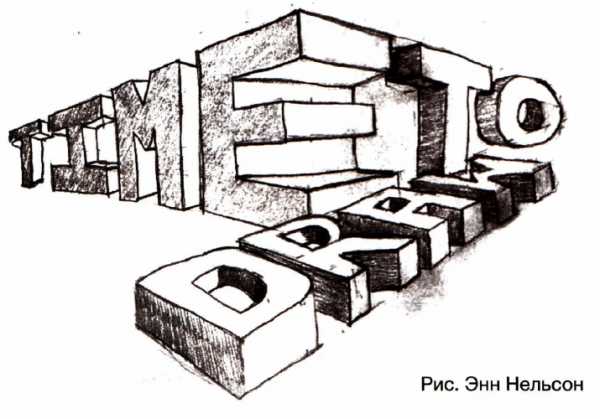
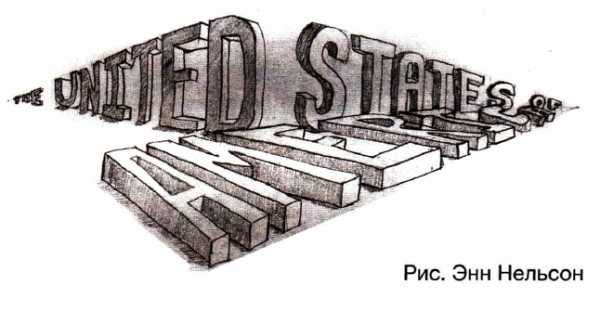
С помощью следующего урока вы перейдете на уровень Леонардо да Винчи, а также сможете нарисовать чей-нибудь портрет.
В одном часе любви целая жизнь.
Ты — жизнь, а я ее люблю!
Дети — это ангелы…
Хорошие друзья, как звезды…
Пусть каждый день с улыбки начинается!
Картинка с надписями.
Мечтай! Улыбайся!
Я каждый раз влюбляюсь и каждый раз в тебя!
Любить — значит видеть чудо!
Звезды сияют ярче…
Залог семейного счастья в доброте….
Пусть будет щедрым Новый Год!
От всего сердца!
Живи с блеском в глазах….
Родная душа…
Жизнь — это все вокруг….
Мое счастье измеряется твоими улыбками.
Счастье — это умение радоваться простым вещам!
Маленькие дети — самые лучшие люди на Земле.
Люби меня всегда…
Счастье….
Чудеса там, где в них верят.
Красивая надпись.
Никто не может грустить…
Крикни — услышит любой!
Спасибо тебе, любимый!
Жизнь — это все вокруг.
Пусть день начнется с доброты!
Красивая надпись.
Слова о любви!
Уметь наслаждаться жизнью, значит жить дважды.
огненный, 3D, анимированный, объемный, текстурный и пр.
Вопрос от пользователя
Привет. Мне нужно написать красивый текст, желательно 3D-шрифтом, но я не владею графическими редакторами (Фотошоп, Gimp и пр.). Пробовал разобраться с инструкциями, но не получилось. Скачивал спец. программу, но в ней не так много образцов шрифтов. Не подскажите, можно ли как-то еще просто и быстро написать красивый текст (без специальных знаний) ?..
Зачем такие жертвы, если написать красиво текст можно без программ и за считанные секунды?